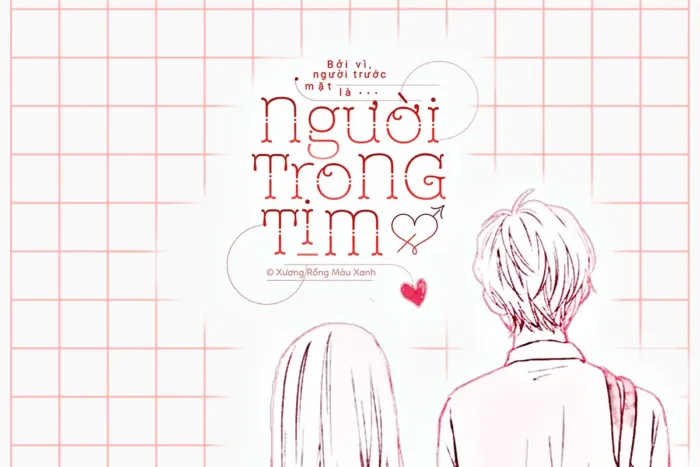
MTD St Friska là một font chữ mang phong cách thanh lịch và lãng mạn, với các đường nét mềm mại, thanh mảnh nhưng vẫn có sự cứng cáp cần thiết. Các ký tự được thiết kế với những đường cong nhẹ nhàng, tạo cảm giác tinh tế và bay bổng. Điểm nhấn của font này là các chi tiết trang trí nhỏ như dấu chấm, đường viền tròn và biểu tượng cách điệu, giúp nó trở nên phù hợp với các thiết kế về tình yêu, truyện tranh, tiểu thuyết lãng mạn hoặc thiệp mời. Đây là một lựa chọn hoàn hảo cho những ai muốn tạo nên sự nhẹ nhàng và cuốn hút trong thiết kế chữ.